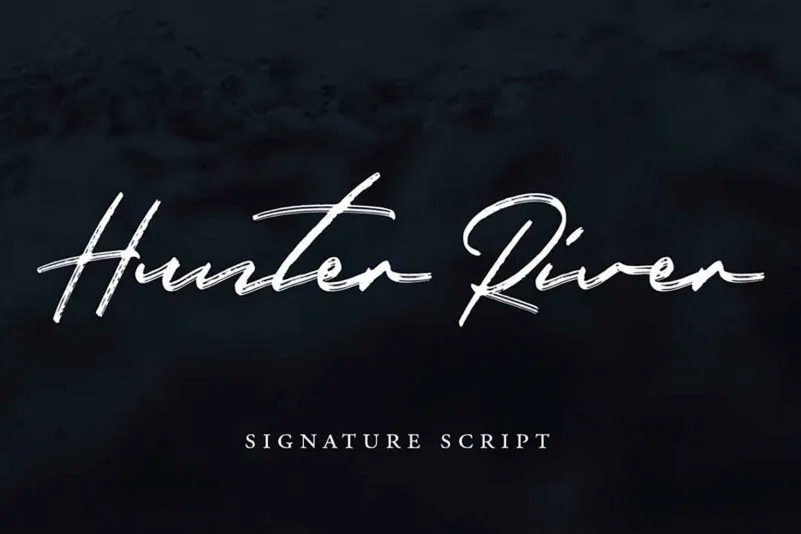
Esta fonte script chamada Hunter River foi criada pela Hustle Supply Co. É perfeitamente adequada para diversas aplicações gráficas, desde a criação de logomarcas e identidades corporativas até as mais delicadas invitações de casamento e cartões de aniversário. Suave e natural, ela possui um toque atraente que certamente chamaria a atenção em postagens sociais criativas e nos maiores desejos de levar o seu design aos olhos do mundo. Ideal para quem busca uma fonte elegante, mas com um ar descontraído, essa font se adapta perfeitamente à criação de cartões de aniversário delicados ou a um layout de postagem social minimalista e envolvente. Ela é ideal tanto para os designers que buscam algo único quanto para quem busca uma fonte simples que seja capaz de dar ao seu design o toque certo de personalidade. Como uma mão na obra, ela é perfeita para aqueles desejando criar um projeto visual que reflita a sua personalidade e estilo de maneira autêntica e intrigante.